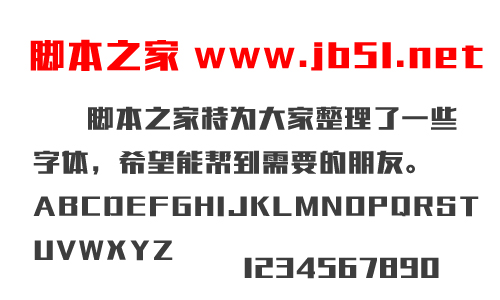
騰祥潮黑簡是騰祥公司自主精心設計開發(fā)的美術黑體。字形結構扁方、端莊,橫豎筆畫粗細比例適度、豎筆粗壯有力,布白均勻、行文貫通,歡迎喜歡騰祥潮黑簡字體的朋友前來下載使用。
字體風格:
字形飽滿富于張力;筆畫硬朗簡潔表現(xiàn)清晰;為了起到裝飾效果左右結構字形在不影響閱讀的前提下,部分點和提、撇和點做連筆畫處理,更好的展現(xiàn)出字形的連貫性和整體感。潮黑筆畫簡潔有力細微處變換靈動,即實用又富有裝飾效果。潮黑為粗黑一款,為了調整黑白空間在筆畫交叉處特別做了墨跡處理,使整體筆畫看起來既粗壯醒目又清晰易讀。適合標題用字,可用于印刷出版、包裝設計、廣告設計、網頁設計等。